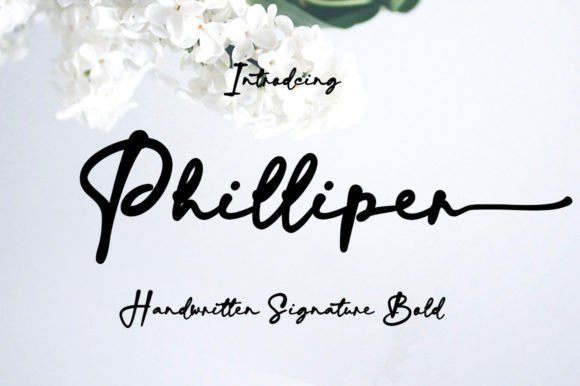
Philliper
หากคุณกำลังมองหาเนื้อหาคุณภาพสูงเช่น Philliper แพ็คเกจพรีเมียมนี้เป็นตัวเลือกที่ยอดเยี่ยมสำหรับโปรเจ็กต์สร้างสรรค์ของคุณ
ไม่ว่าคุณจะสร้างผลิตภัณฑ์ POD (Print on Demand) คำเชิญงานแต่งงาน หรือกราฟิกโซเชียลมีเดีย Philliper ก็เหมาะสมอย่างยิ่ง